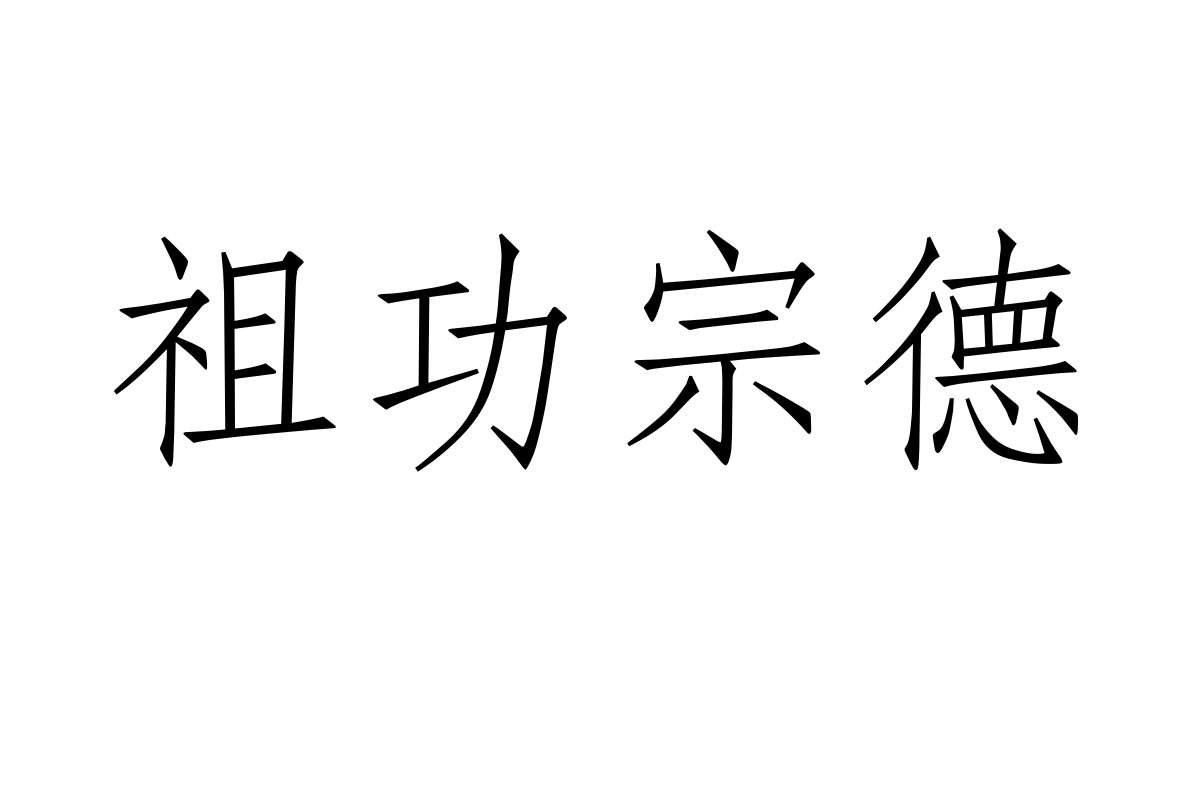
汉仪仿宋繁字体是一款由汉仪公司推出的仿宋体中文简体字库,具有丰富的字形资源和多种应用场景。该字体采用现代化设计,线条流畅自然,结构严谨规范,适用于各种印刷品、包装、广告、书籍、杂志等场合。其特点包括:
1. 字形丰富多样:汉仪仿宋繁字体拥有多种字形,如楷书、行书、草书等,满足不同用户的需求。
2. 字形规范统一:该字体遵循国家汉字规范,字形规范统一,易于识别和阅读。
4. 适用范围广泛:该字体适用于各种印刷品、包装、广告、书籍、杂志等场合,具有较高的实用价值。